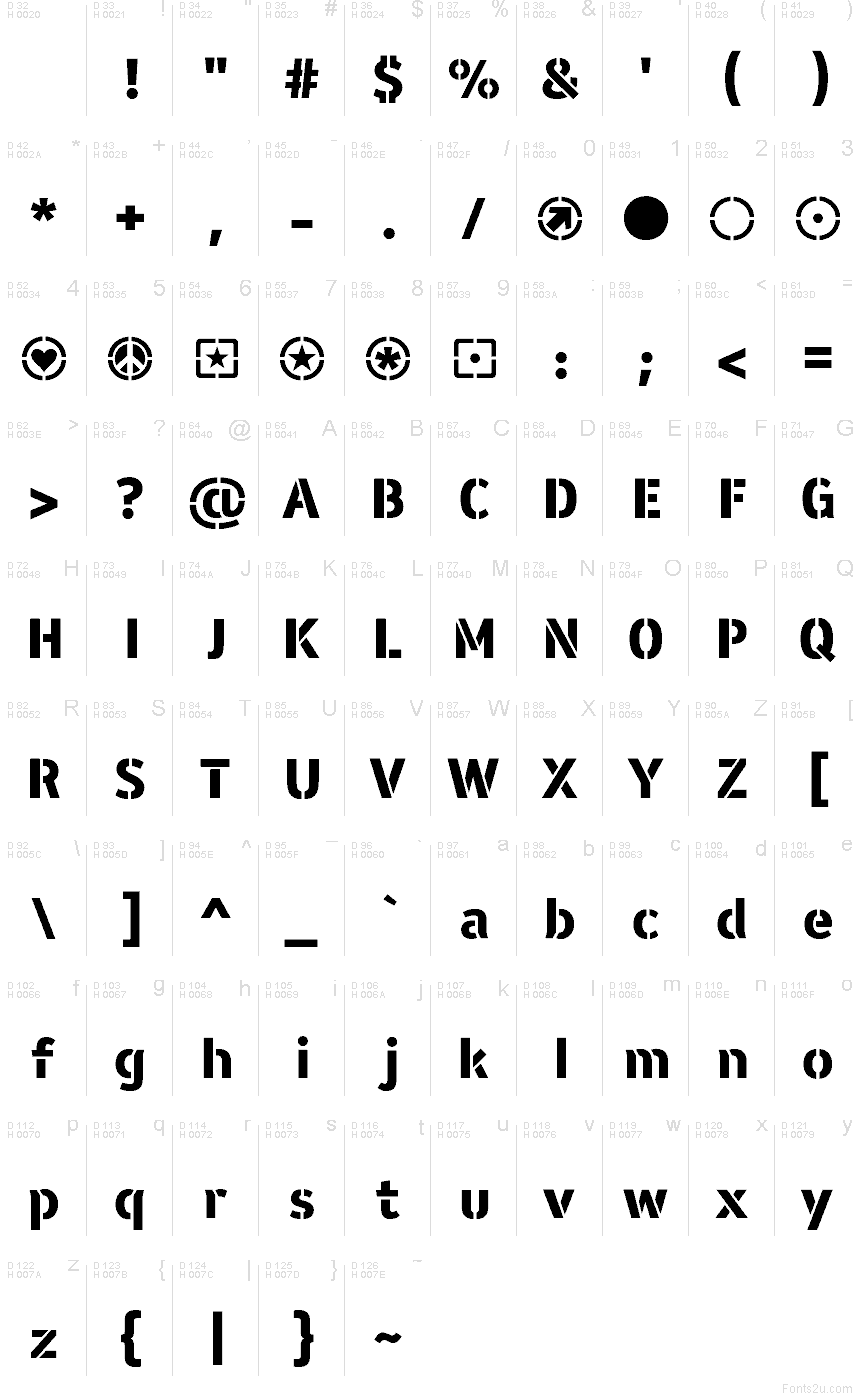
WARFIELD Bold
フォント「Warfield Bold」は、Fernando HaroによるdeFharoのWarfieldファミリーに属する無料のミリタリーステンシル書体です。重厚なブロック感と鋭く抜かれた隙間が効いた、存在感の強いデザインに仕上がっています。荒れた金属にスプレーで吹き付けたような字形は、角張ったフォルム、タイトな字間、クリーンなカットが特徴。離れた場所からでもひと目で読める視認性を備えています。形のリズムには規律があり、メッセージにタフでタクティカルな空気を与えながら、ありがちな軍モノ表現に寄りすぎません。
Warfield Boldなら、タクティカルギアのブランディング、FPSゲームのタイトル、イベントポスター、車両マーキングのモックアップ、無骨なSNSグラフィックやパッケージデザインまで幅広く対応できます。この無料フォントが真価を発揮するのは、大きく太い見出し。本文にはシンプルなグロテスク系サンセリフを合わせて、視覚的なインパクトはWarfield Boldに任せるのがおすすめです。
WARFIELD is, by definition, a stencil typeface, drawing from its military and industrial heritage, but shedding any aggressiveness to embrace absolute legibility.
It is a contemporary sans-serif that is not only read but also felt, proudly displaying the breaks, bridges, and interruptions that define it, giving it a straight and solemn bearing.
From the ethereal subtlety of Light to the resounding authority of Black, Warfield offers seven weights designed to withstand any creative battle.